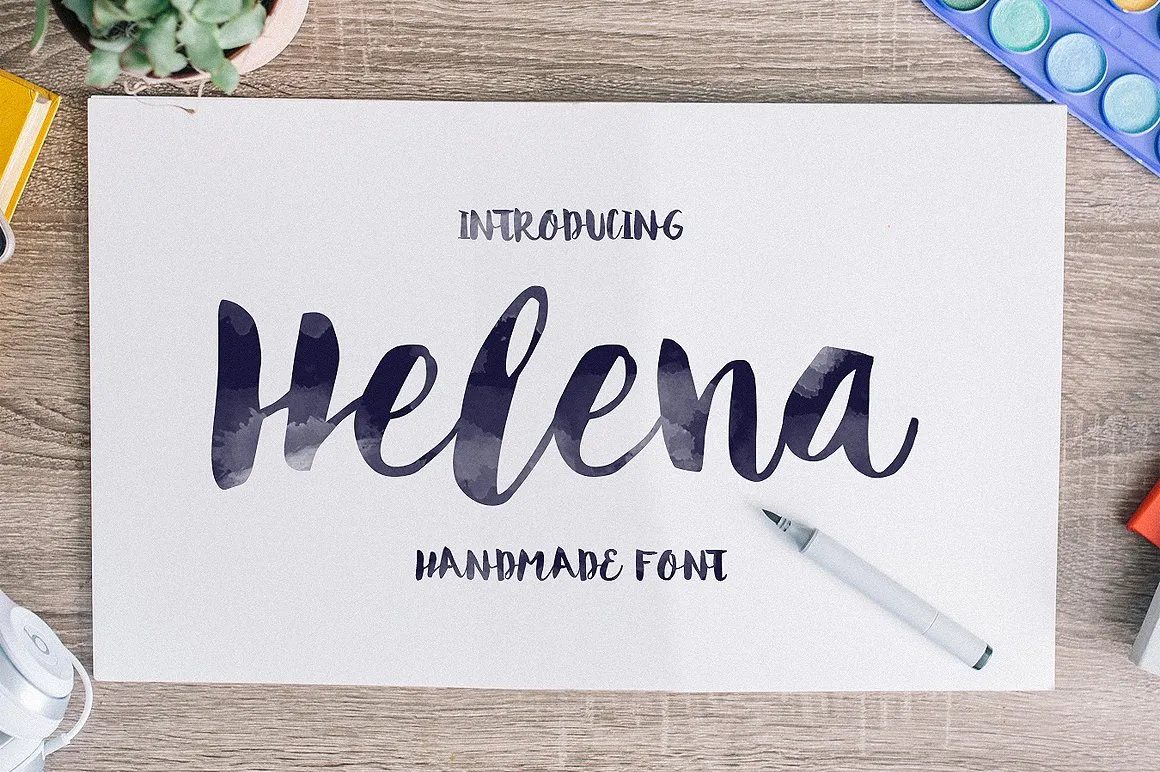
A Helena Font é uma escolha perfeita para quem busca adicionar um toque autêntico à sua identidade visual. Seja para criações de estaçãoamento, logotipos ou qualquer outro tipo de design que exija texto impresso em materiais específicos, essa fonte oferece inúmeras possibilidades. Helena é um tópico novo e repleto de recursos criados por Hamilton. Perfumada para os designers que desejam uma experiência única ao criar elementos gráficos para roupas ou materiais impressos, esta fonte abrange desde as mais sutiles até as mais expressivas. A Helena Font é versátil e intuitiva, permitindo o uso de múltiplos idiomas e combinando-se facilmente com designs variados. Com a Helena Font, você pode adicionar texto à sua camisa desejada ou criar um logotipo onde desejar inserir conteúdo textual. Isso torna-a uma fonte indispensável tanto para designers profissionais quanto para amantes de design em busca da perfeição na criação de suas criações. Ela é uma ótima escolha se você está procurando por algo mais que a maioria das outras fuentes possuem, oferecendo um toque único e autêntico ao seu trabalho.